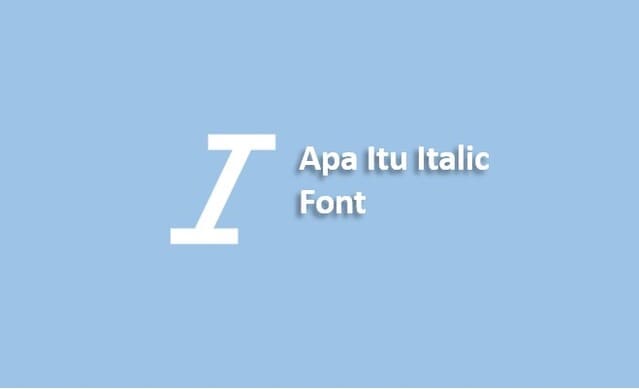
Apa Itu Italic Font – Font italic adalah gaya huruf yang miring atau condong ke sisi kanan. Saat menggunakan huruf miring, setiap karakter akan memiliki kemiringan ke arah kanan, memberikan tampilan yang berbeda dari huruf biasa. Penggunaan teks miring pada seringkali digunakan untuk menekankan kata atau frase tertentu, memberikan nuansa yang berbeda, atau untuk membedakan antara elemen teks yang berbeda. Contohnya, dalam teks cetak, judul buku atau film sering ditulis dalam huruf miring untuk menonjolkan mereka dari teks di sekitarnya.
Selain itu, font italic juga sering digunakan dalam penulisan beberapa jenis dokumen ilmiah atau karya tulis lainnya untuk menunjukkan kata-kata asing, istilah teknis, atau judul karya seni.
Pemakaian Font Italic juga dapat membantu untuk membedakan elemen pada teks seperti, dalam tulisan panjang sering ditulis dalam font italic untuk membadakan dari teks yang lainya. Dan juga, font italic digunakan oleh beberapa penulis untuk menyampaikan dialog dalam tulisan mereka agar dapat memberikan efek visual yang mendukung nada atau suasana saat percakapan pada dialog mereka.
Penggunaan font miring sangat bervariasi tergantung pada konteks dan preferensi penulis. Lalu, bagaimana cara menggunakan italic font?
Dengan kemampuannya untuk menekankan, membedakan, dan memberikan nuansa pada teks, font miring bukan sekadar gaya huruf, melainkan alat ekspresif yang penting dalam dunia tulisan dan desain. Dari penggunaannya yang efektif dalam menonjolkan kata kunci hingga memberikan identitas pada judul-judul karya seni. Di balik kemiringannya yang sederhana, kekuatan tersembunyi untuk menyampaikan arti dan memberikan daya tarik visual pada setiap kalimat. Demikian Penjelasan singkat tentang Apa Itu Italic Font, Semoga Bermanfaat